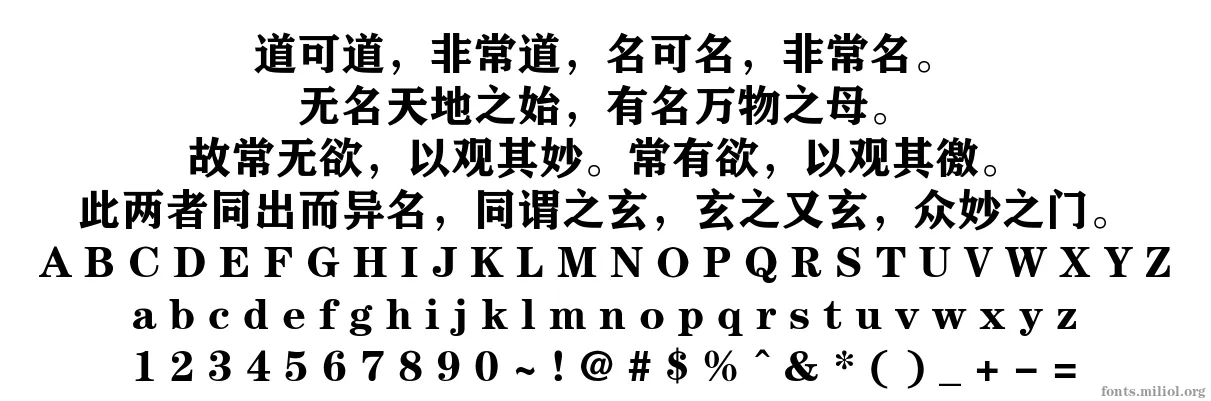
**方正粗黑宋简体字体简介**
方正粗黑宋简体(FZCuHeiSongS-B-GB)是一款兼具传统宋体结构与现代黑体力度的创意字体,由方正字库设计开发。其笔画粗壮有力,横平竖直的笔形保留了宋体的典雅韵味,而加粗的线条又赋予其黑体的视觉冲击力,适合用于标题、广告、品牌宣传等需要突出表现力的场景。字体编码符合GB2312标准,支持简体中文及常用符号,兼容性广泛。
该字体风格庄重而不失灵动,既能体现文化底蕴,又能适应现代设计需求。文件命名中的“FZCHSJW--GB1-0”为其内部版本标识,用户需通过正规渠道获取授权,确保合法使用。无论是印刷品还是数字媒体,方正粗黑宋简体都能为作品增添独特的视觉张力。